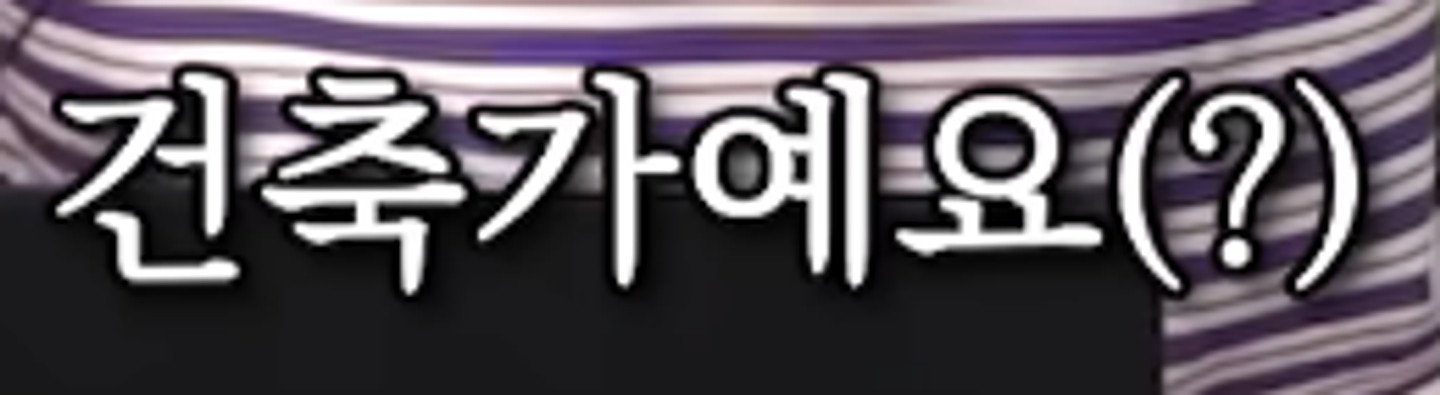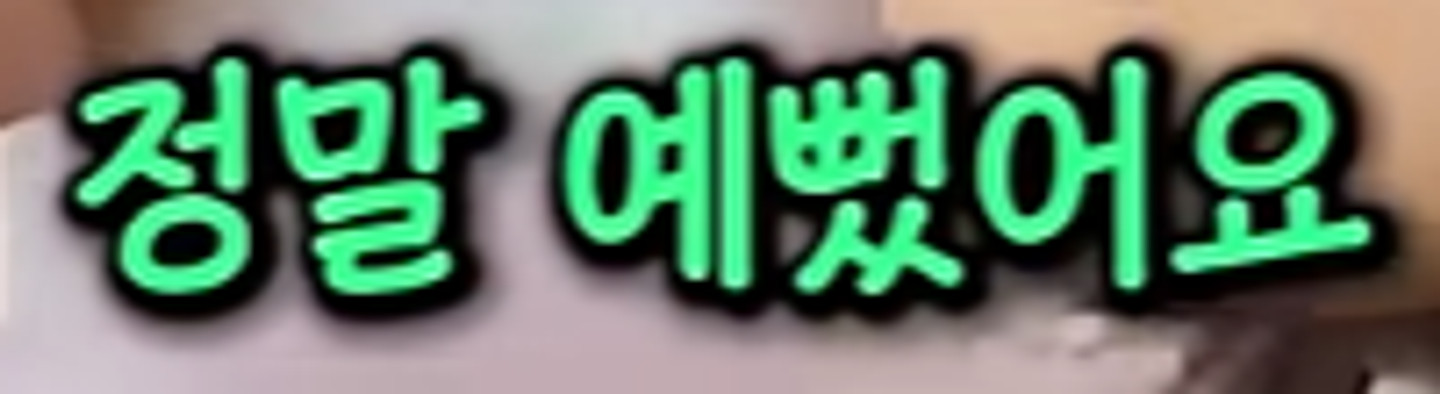
페이퍼로지체입니다! 획은 3-5 point로 준거 같고, 그림자는 블러효과 없이 120도 각도로 밑으로 방향가게 효과 준거 같네요! 저도 폰트 만드는건 잘 모르지만 손글씨로 만들고 싶으시면 그리운 사이트에서 폰트 만드는거 결제 후 가능하시고, 본격적으로 만드시려면 글립스(맥 전용) 이런 유료 프로그램으로 만드는 걸로 알고 있습니다!